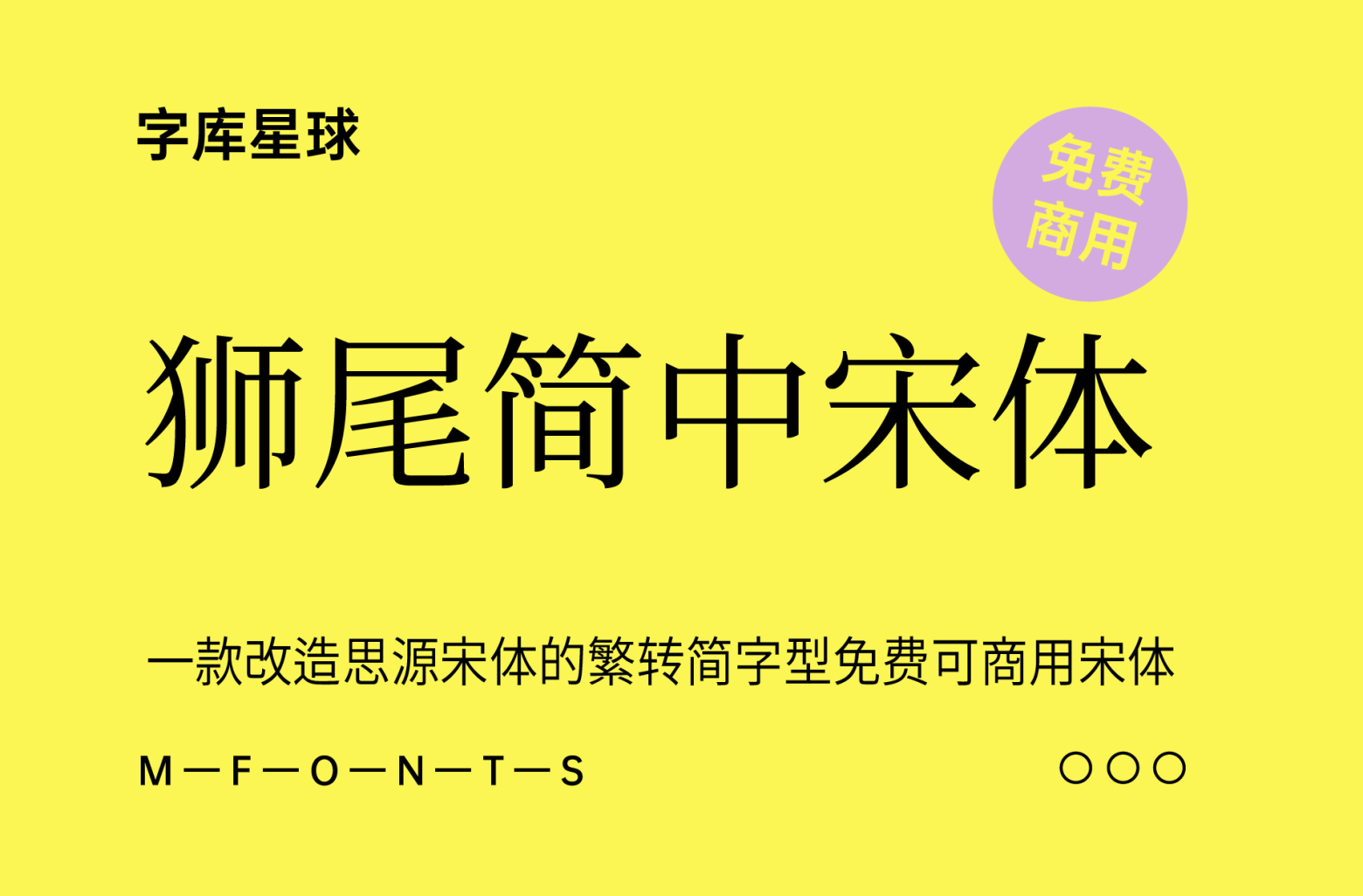
狮尾简中宋体
狮尾简中宋体基于思源宋体的繁转简字型;可以免费商用,欢迎大家自由应用、自由改作!
狮尾简腿黑体的特色是:繁体字转成简体字的字型档,由于是转成简体,所以能处理「一简对多繁」。
狮尾简中宋体
说明:繁中的「发」和「发」在简中都是「发」;繁中的「后」和「后」简中都是「后」。
「狮尾繁中宋体」设计上针对笔画粗细支援7种字重,所以不论大标、小标、简单的段落排版都能清晰辨识。